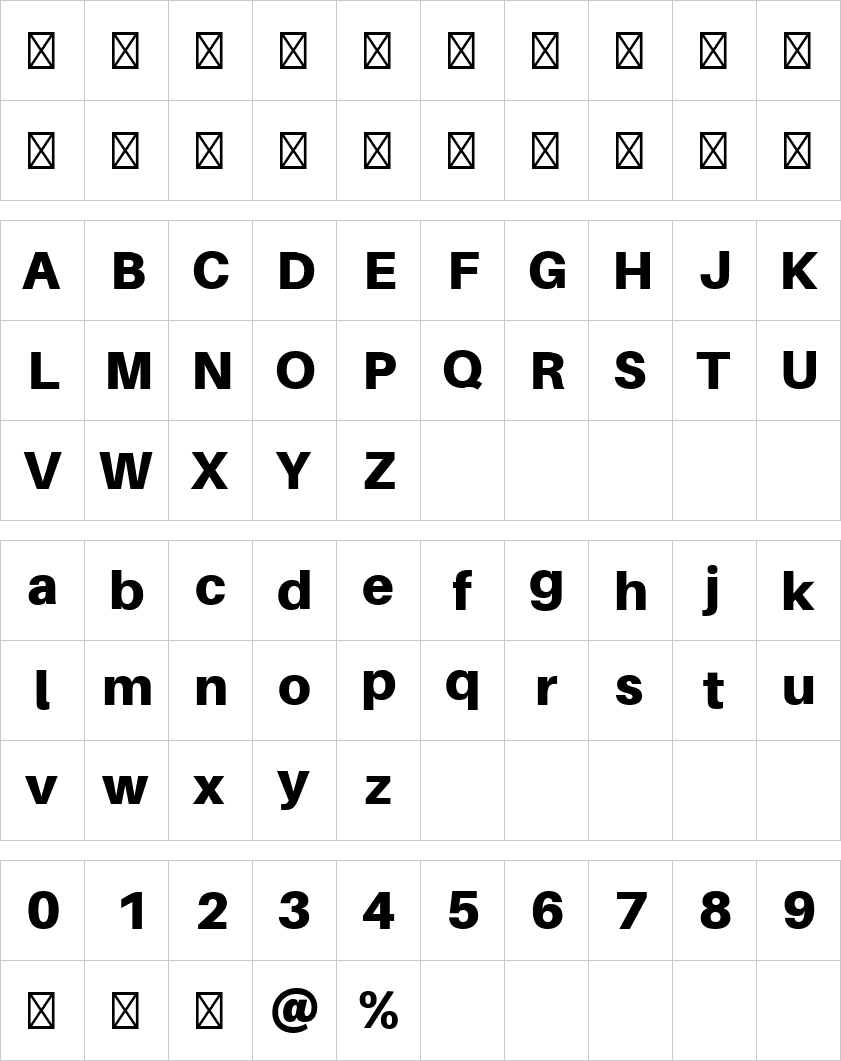
Aileron
Aileron 是一种无衬线字体,基于 Helvetica 等新怪诞字体,并添加了我自己的解释。
作为对文字的调整,字母之间的间距稍微变宽,小写字母“L”的末端已弯曲,以便更容易将其与大写字母“I”区分开。
另外,“i”、“j”、句号等圆点都被做成了圆形,弯曲的部分也被处理成类似回旋曲线的形状,整体给人一种柔和的感觉。在设计上,它与 Helvetica 类似,但在概念上,它与 Univers 更相似。
此外,这是我们第一次准备斜体版本的点冒号字体。基本上,它是机械倾斜的,但已经进行了视觉修正,因此不会感到奇怪。
利用多重主控的优势,提供从超轻到黑色的 8 个重量级别。我认为它可以用于多种情况。